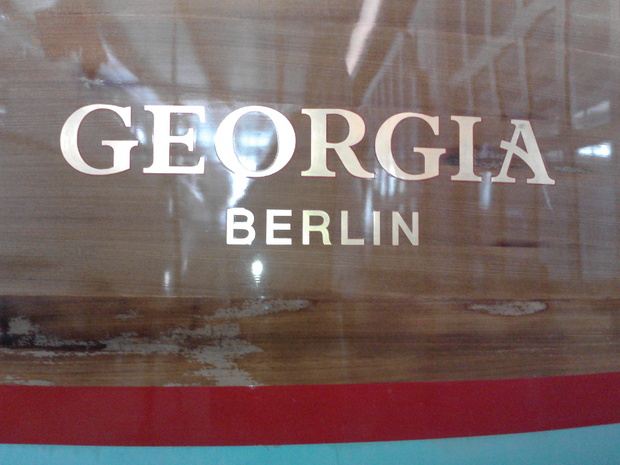
Suche dringend diese Schrift
Ich bin auf der Suche nach dieser Schift:
Habe es schon bei what the font versucht, aber ohne Erfolg.
Kennt jemand diese Schrift? Es muss unbedingt genau diese sein.
Das A ist ja sehr auffällig.
Woher stammt das und gibt es mehr Buchstaben zu sehen?
Das ist ein Schriftzug von einem Boot.
Der wurde jetzt abgeschliffen und ich soll ihn erneuern. Habe leider nur ein Foto.
Hier das Original.
Ich hab das mal entzerrt …
GEORGI könnte aus der Bembo sein. Das A aus einem Benguiat-Klon?
Ich denke mal aus dem A der "Lapture-Bold" kann man einiges machen um zum Ergebnis zu kommen.
Ich hatte auch schon befürchtet, dass das A nicht so richtig passt.
Jetzt habe ich es einfach mit Hilfe des Fotos nachgebaut.
Habe mir das Boot gestern noch mal selbst angesehen und der Abdruck vom A ist glücklicherweise am wenigsten zu erkennen.
Es wird also kaum auffallen.